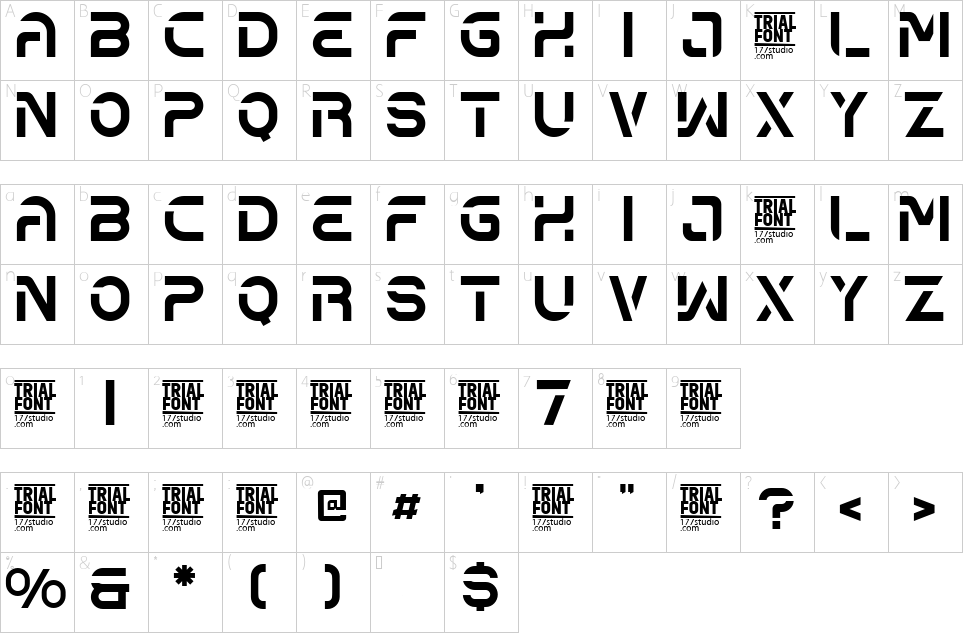
Descubra a elegância e o poder de design da Mentor Reward Font, uma opção gratuita e versátil para seu próximo projeto. Desenvolvida pela 177studio.com, esta fonte gráfica traz uma variedade de opções para personalizar seu texto de maneira única e sofisticada. Com 1,148 downloads registrados, é evidente que esta font oferece uma qualidade que vale a atenção. Ideal para trabalhos profissionais e criativos, a Mentor Reward se destaca por sua versatilidade e facilidade de uso. Se você está procurando por uma fonte de qualidade que não faça seu orçamento tremer, esta é uma fonte que merece ser incluída na sua coleção. Baixe agora e descubra o potencial de personalizar seu design com esta font excepcional.